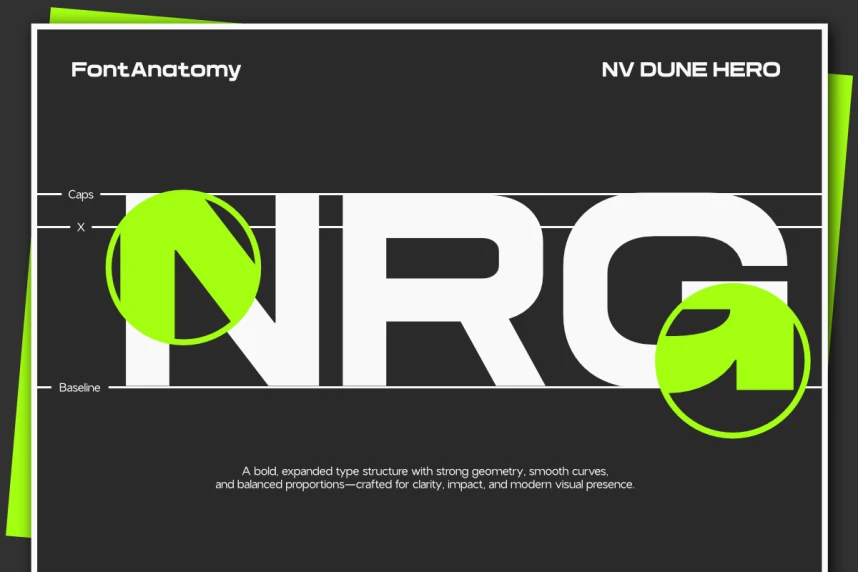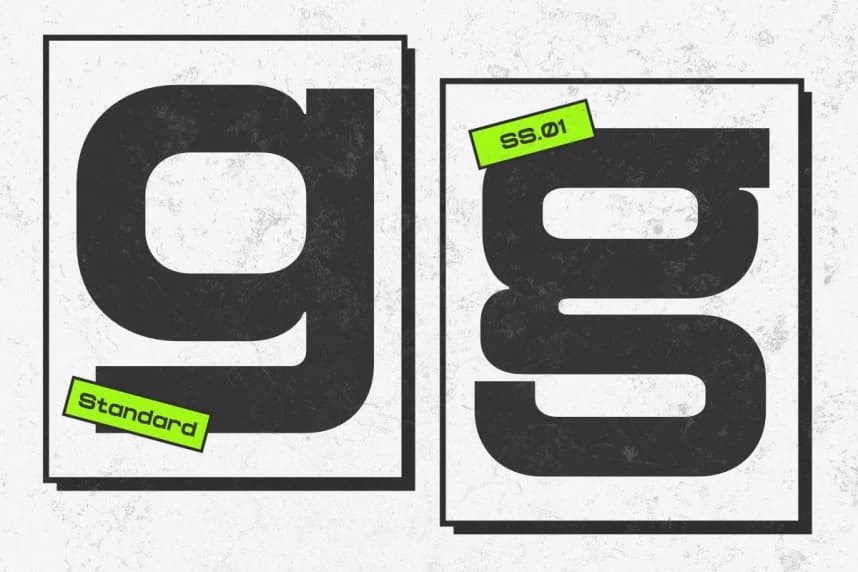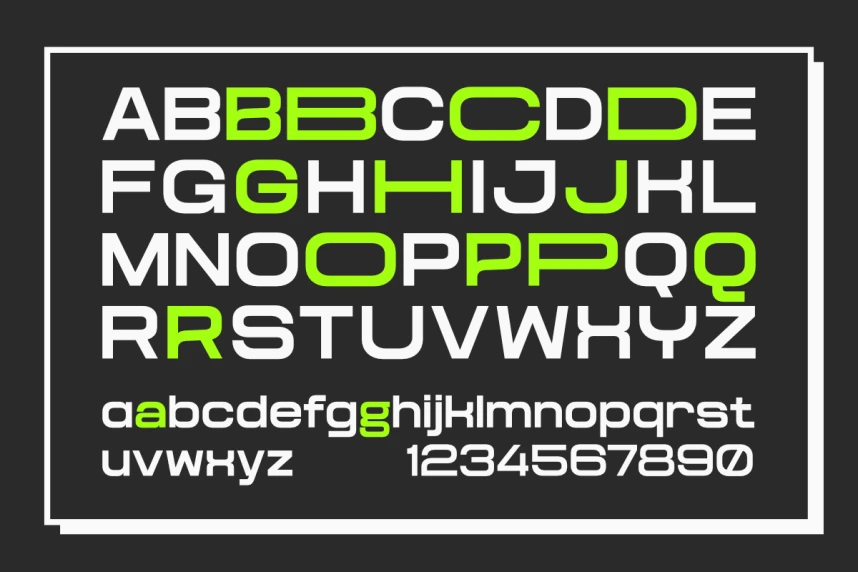
NV Dune Hero Yazı Tipi Ailesi
NV Dune Hero Yazı Tipi Ailesi - Expand Sans Serif Yazı Tipi Ailesi, modern hassasiyetle güçlü bir görsel etki yaratmak için tasarlanmış cesur ve ifadeli genişletilmiş bir tip sistemi. NovaraType tarafından geliştirilmiş olan NV Dune Hero geniş oranlar ve geometrik dengeyi bir araya getirir.
NV Dune Hero Font Family - Expand Sans Serif Font Family, cesur ve ifade gücü yüksek genişletilmiş bir tip sistemi olup modern hassasiyetle güçlü görsel etki yaratmak için tasarlanmıştır. NovaraType tarafından geliştirilen NV Dune Hero, geniş oranlar ve geometrik dengeyi bir araya getirir